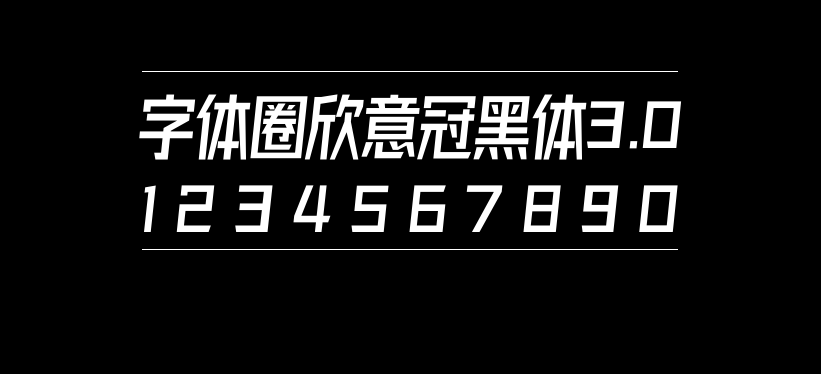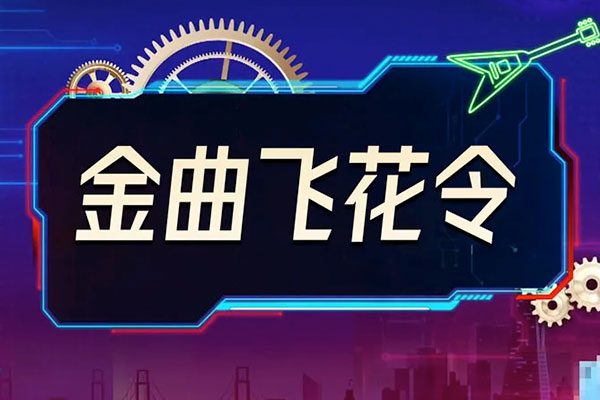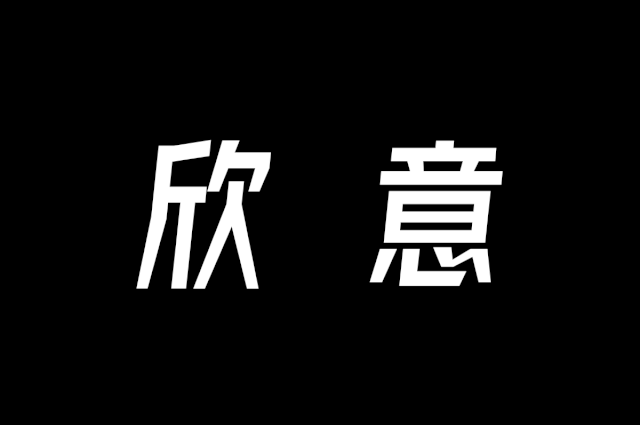
字体圈欣意冠黑体3.0
字体圈欣意冠黑体是国内字体设计师邹乐伟创作的一款优秀的字体,字形硬朗潇洒,自2.0版本发布后已被广泛使用,今天他又更新了字体,发布了3.0版本,同样是免费商用。
全新3.0更新了什么?
1 更改部分字形设计
2 重新设计西文数字标点部分
3 添加3000+个繁体字符,现在字符数量是将近10000个了
4 还原字形默认大小
5 添加了生僻字“biang”
添加3000+个繁体字符
繁体部分是这次更新的重心,前前后后白天也弄晚上也弄,也花了四个月的时间。中文现涵盖9169字,另按需添加若干生僻字,56个英文10个数字,标点若干。虽然增加繁体只有三千多字,比简体少了整整一半,但是做起来比简体复杂得多,很多字的笔画非常多,甚至比简体多好几倍,所以工作量并没有想象中相应的减少。
字体圈欣意冠黑体3.0